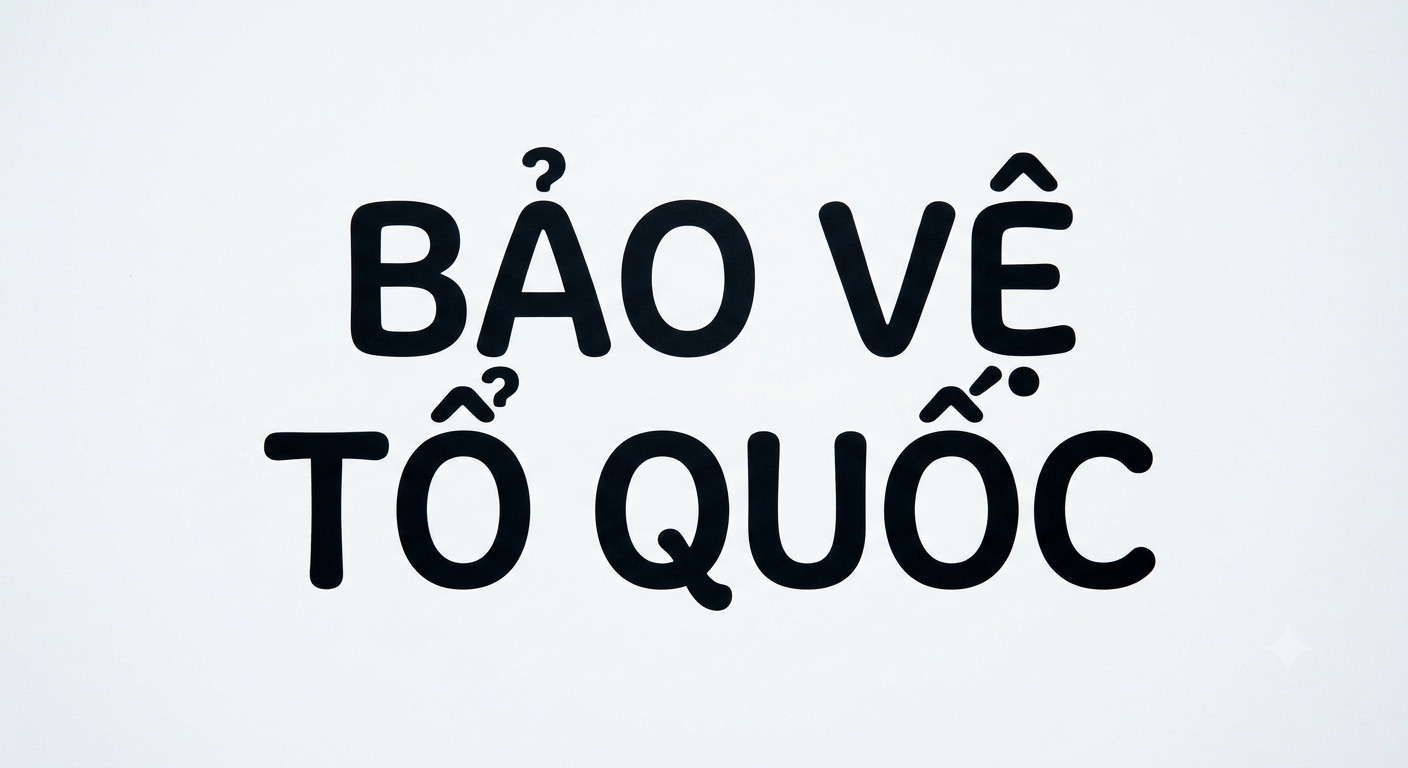
Designer thường gặp lỗi khi sử dụng font UEE do thiếu dấu tiếng Việt hoặc đường nét chữ bị vỡ khi in trên các chất liệu như kim loại, hộp quà công nghệ. Những lỗi hiển thị này có thể làm giảm tính đồng nhất của bộ nhận diện thương hiệu, ảnh hưởng đến sự chuyên nghiệp trong thiết kế.
Font UEE là gì?
Font UEE (thường được biết đến phổ biến qua bản UTM UEE) là một phông chữ thuộc dòng Sans-serif hiện đại với cấu trúc hình học cân đối và vững chãi. Đặc trưng của bộ chữ này là các nét thẳng dứt khoát kết hợp với những đường bo góc tinh tế, tạo nên vẻ ngoài minh bạch, quyết đoán và hợp thời. Đây là lựa chọn thường xuyên cho các thiết kế logo công ty xây dựng, bao bì thiết bị điện tử hoặc các tiêu đề hồ sơ năng lực yêu cầu sự rõ ràng và uy tín.
Tại thị trường Việt Nam, phông chữ này được ưa chuộng nhờ khả năng hiển thị tốt trên cả màn hình kỹ thuật số và các ấn phẩm in ấn khổ lớn. Tuy nhiên, nếu không sử dụng bản việt hóa chuẩn, các ký tự như “đ, ư, ơ” thường bị lỗi hiển thị chân chữ hoặc dấu thanh bị lệch vị trí. Bản Font uee việt hoá tại In Viva đã được xử lý kỹ thuật Kerning, đảm bảo ngôn ngữ tiếng Việt hiển thị thẩm mỹ trên mọi chất liệu bao bì cao cấp, giúp doanh nghiệp xây dựng hình ảnh thương hiệu nhất quán.
Font UEE đẹp 01
Lưu ý: Với cấu trúc chữ hiện đại của UEE, bạn nên ưu tiên sử dụng các màu đơn sắc hoặc tông màu trung tính để tôn vinh sự chuyên nghiệp và tối giản của bộ phông này trên hộp quà tặng.
5 ứng dụng của font UEE trong thiết kế và in ấn
Vẻ đẹp mạnh mẽ và hiện đại của phông chữ UEE giúp các sản phẩm bao bì, quà tặng doanh nghiệp trở nên chuyên nghiệp hơn khi kết hợp cùng các kỹ thuật in ấn và gia công phù hợp:
• Thiết kế bao bì thiết bị điện tử và linh kiện: UEE phù hợp để thể hiện tên thương hiệu, mã sản phẩm hoặc thông tin kỹ thuật trên hộp giấy, hộp cứng đựng thiết bị công nghệ. Cấu trúc chữ rõ ràng giúp nội dung dễ đọc, phù hợp với phong cách thiết kế hiện đại.
• Sản xuất set quà tặng văn phòng in logo: Logo sử dụng font UEE khi in UV trên bình giữ nhiệt kim loại, sạc dự phòng hoặc khắc laser trên bút ký, sổ tay giúp tạo điểm nhấn chuyên nghiệp cho các bộ quà tặng doanh nghiệp.
• In ấn túi giấy thương hiệu xây dựng và nội thất: Sử dụng phông chữ UEE cho logo, tên thương hiệu hoặc thông tin liên hệ trên túi giấy Ivory, Kraft giúp bộ nhận diện thể hiện phong cách mạnh mẽ, phù hợp với các doanh nghiệp kỹ thuật và kiến trúc.
• Trang trí bảng biển và mô hình dự án: Với định dạng vector, font UEE có thể sử dụng cho các thiết kế bảng hiệu, backdrop hoặc mô hình trưng bày cần phóng lớn. Đường nét chữ được giữ rõ ràng, giúp không gian thương hiệu có sự đồng nhất về hình ảnh.
• Sản xuất kỷ niệm chương và huy hiệu: Font UEE Bold phù hợp để khắc tên doanh nghiệp, thông tin sự kiện trên các chất liệu như pha lê, kim loại hoặc mica, tạo điểm nhấn cho các sản phẩm vinh danh và quà tặng lưu niệm.
Bảng kí tự font UEE
Để font UEE giữ được độ sắc nét khi chuyển từ file thiết kế sang sản phẩm thực tế, designer cần chú ý các yếu tố kỹ thuật sau:
• Kiểm soát độ dày nét chữ: UEE có các biến thể với phần nét khá chắc. Khi in trên hộp quà nền tối hoặc chất liệu có độ hút mực cao, nên kiểm tra kích thước chữ phù hợp để hạn chế tình trạng bít nét ở các chi tiết nhỏ.
• Tối ưu đường Path cho gia công dập nổi: Khi sử dụng UEE làm logo trên hộp cứng, file vector cần được xử lý các điểm neo và góc chữ trước khi tạo khuôn. Việc tối ưu đường path giúp quá trình dập nổi tái hiện rõ hình dạng chữ, hạn chế ảnh hưởng đến bề mặt giấy trong quá trình gia công.
• Điều chỉnh khoảng cách ký tự (Tracking): UEE có cấu trúc chữ cân đối, tuy nhiên khi ứng dụng trên các bề mặt cong như bình giữ nhiệt hoặc ly sứ, designer nên cân chỉnh khoảng cách giữa các ký tự để logo hiển thị hài hòa hơn.